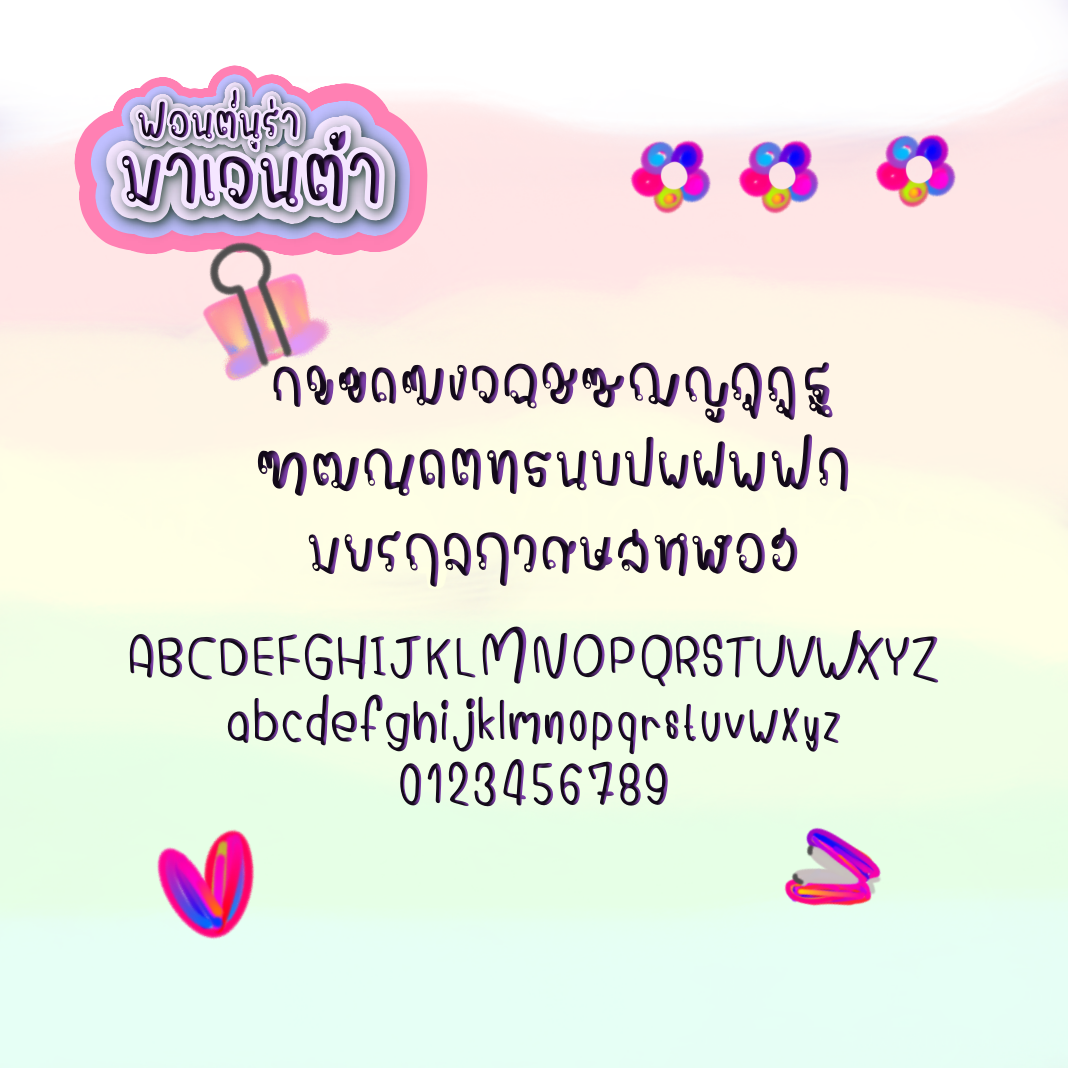
นูร่ามาเจนต้า (Nura magenta)
ฟอนต์ลายมือน่ารัก ฟอนต์ตัวเรียว มีขนาดฟอนต์บางที่ปลาย ตัวเอียงลงเล็กน้อย   ทำโปรโมทสินค้า มีด้วยกัน  3 น้ำหนัก  คือ บาง ปกติ หนา